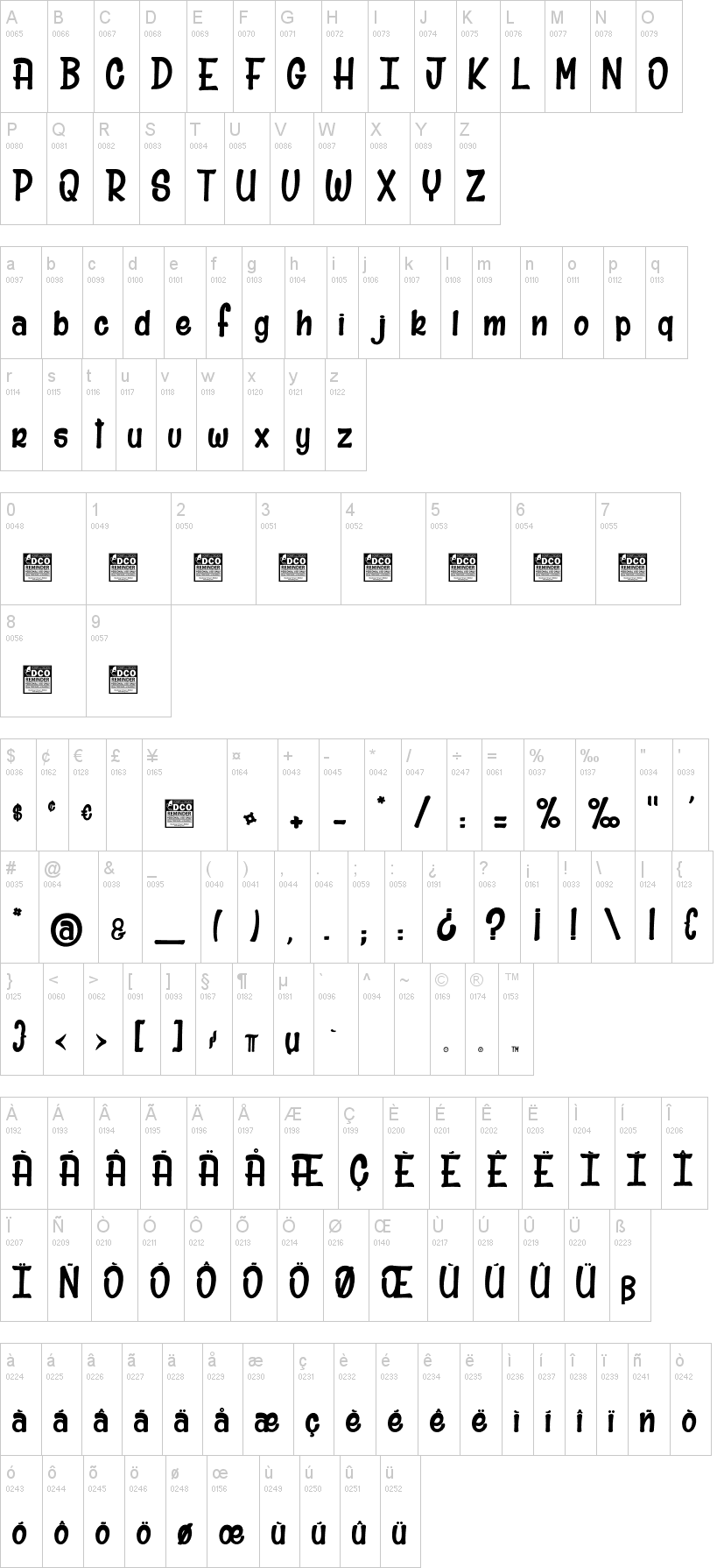
Mr Sunshine
Mr Sunshine 是一种非常有趣和充满活力的手写字体,它由 Comicraft 设计师 Richard Starkings 创造。这种字体看起来像是手写的,而且字母有点倾斜,给人一种轻松愉快的感觉。它的特点是线条流畅,具有很强的可读性和良好的排版效果,同时又不失个性。Mr Sunshine 字体非常适合用于各种设计项目,如海报、标志、手册等,特别是那些需要表达乐观、积极、阳光的信息的设计。总的来说,Mr Sunshine 字体是一种非常有趣和多用途的字体。
Mr Sunshine是一款非常不错的手写艺术字体,具有很好的视觉感,适合于文化类的宣传设计、商业类品牌的广告和产品包装设计以及个性化文字排版等较多场景。